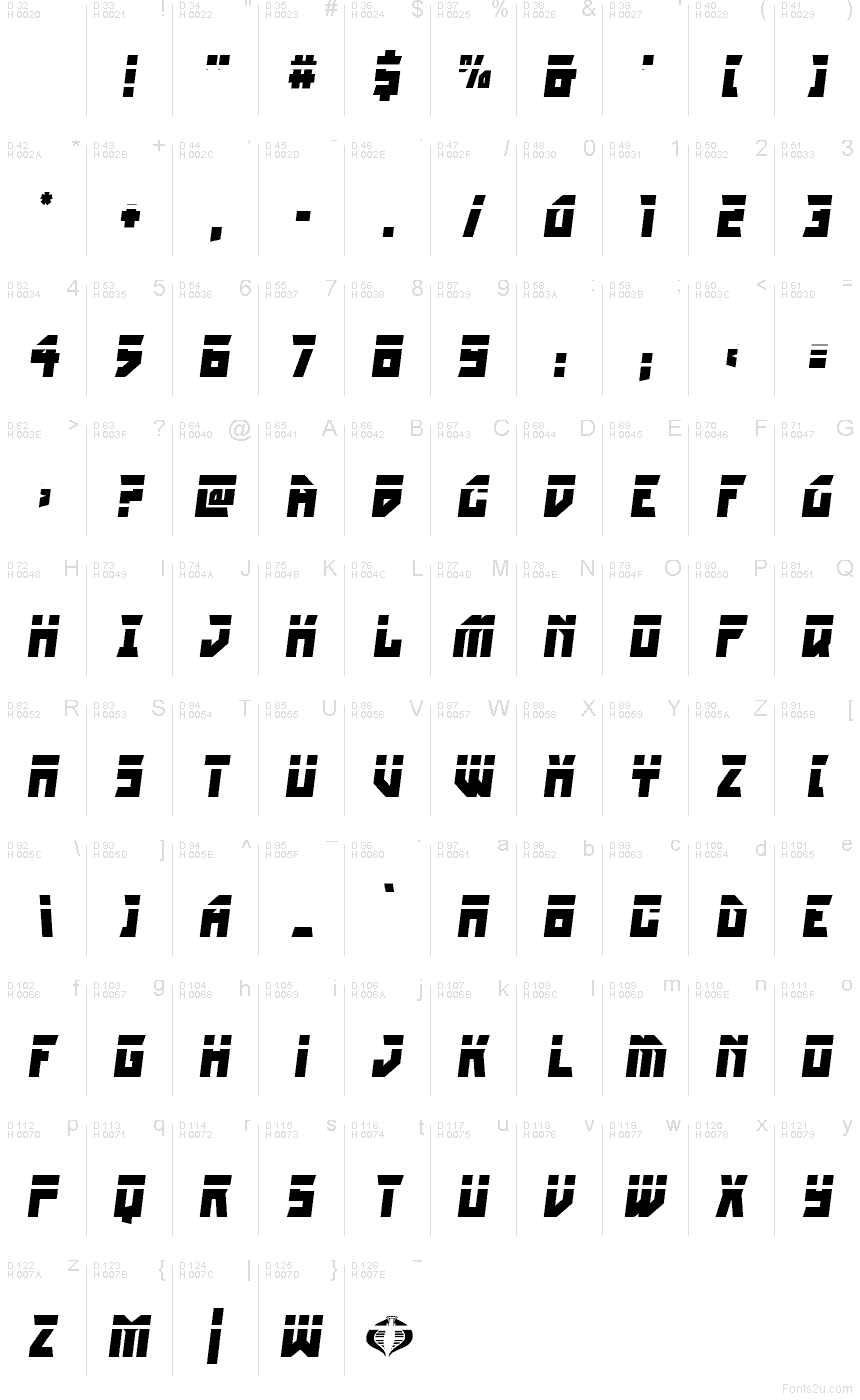
Omni-cobra Laser
Omni-Cobra Laser par Iconian Fonts est une police d'affichage techno gratuite, caractérisée par des coupes angulaires tranchantes, des incisions obliques traversant les traits et des formes géométriques compactes qui évoquent un style de découpe laser. Les lettres suivent un rythme mécanique et saccadé, avec des ouvertures étroites et des angles vifs qui confèrent à l'ensemble un aspect rigide et codifié.
Omni-Cobra Laser convient parfaitement aux affiches de science-fiction, aux titres de jeux, aux pochettes d'albums, aux visuels d'e-sport et aux flyers d'événements futuristes, où ses formes de métal découpé peuvent porter l'idée graphique principale. Cette police gratuite est également idéale pour les logos, les titres et la signalétique nécessitant une esthétique techno tranchée, sans fioritures inutiles.